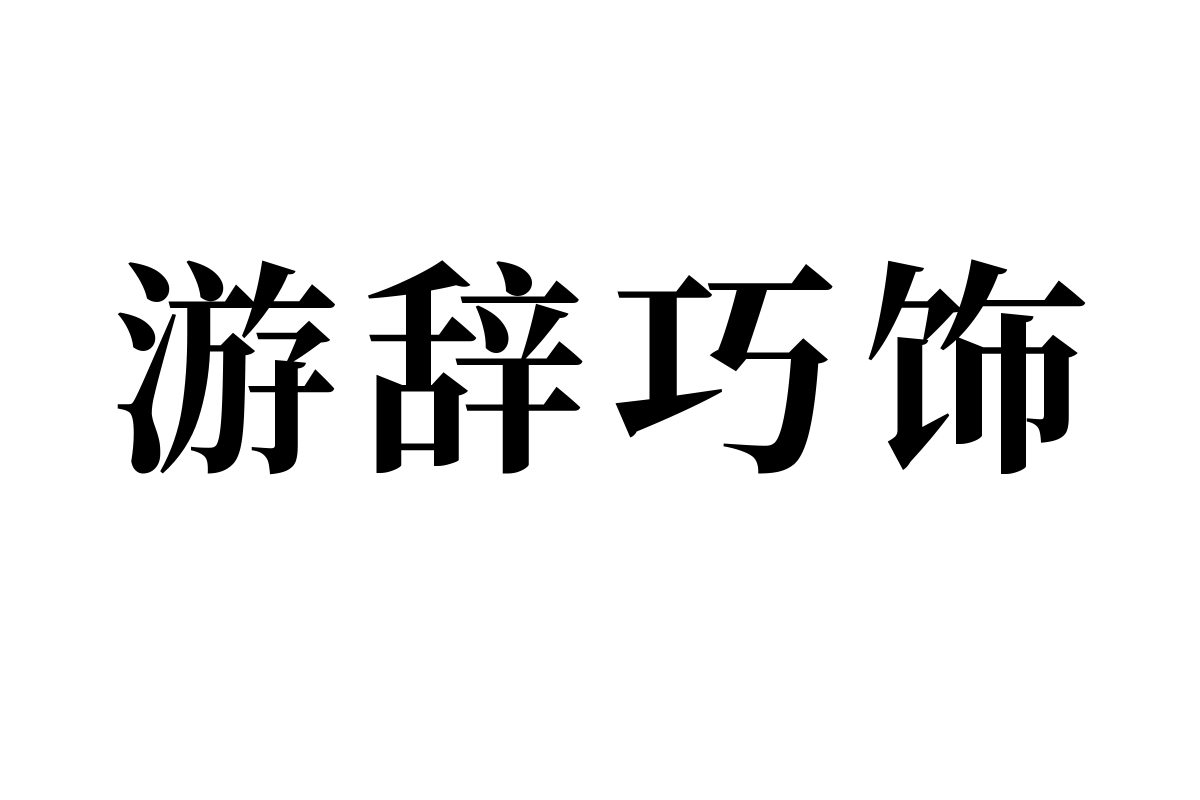
三极字海宋GBK字体是一款适用于中文字符的字体,具有独特的设计和风格。这款字体采用了传统的宋体结构,但进行了一些创新和改良,使其更加符合现代审美和使用需求。
1. 字形:三极字海宋GBK字体的字形规整、清晰,每个字符都易于辨识和阅读。它保留了宋体的基本特点,如横竖撇捺等基本笔画,同时对某些笔画进行了简化和优化,使得整体效果更加美观。
2. 风格:该字体风格古朴典雅,适合用于需要展示传统文化和艺术氛围的场合。它的线条流畅自然,给人一种宁静、舒适的感觉,能够很好地融入各种设计元素中。